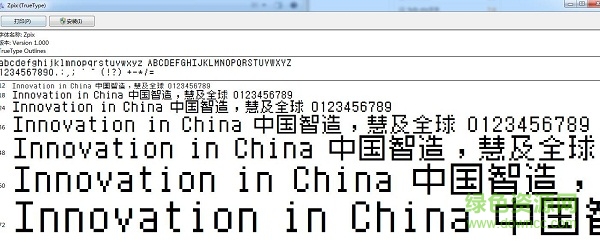
zpix字體是一款實(shí)用的中文像素字體,粗細(xì)適中,筆畫干凈大氣,清晰度高,滿滿的現(xiàn)代感,適用于LED屏幕以及科技主題的廣告設(shè)計方面,需要的小伙伴們快來綠色資源網(wǎng)下載吧!
具有規(guī)范、工整,容易辨認(rèn)的特點(diǎn),給人以簡潔爽朗的現(xiàn)代感,適合于機(jī)械科技等主題。